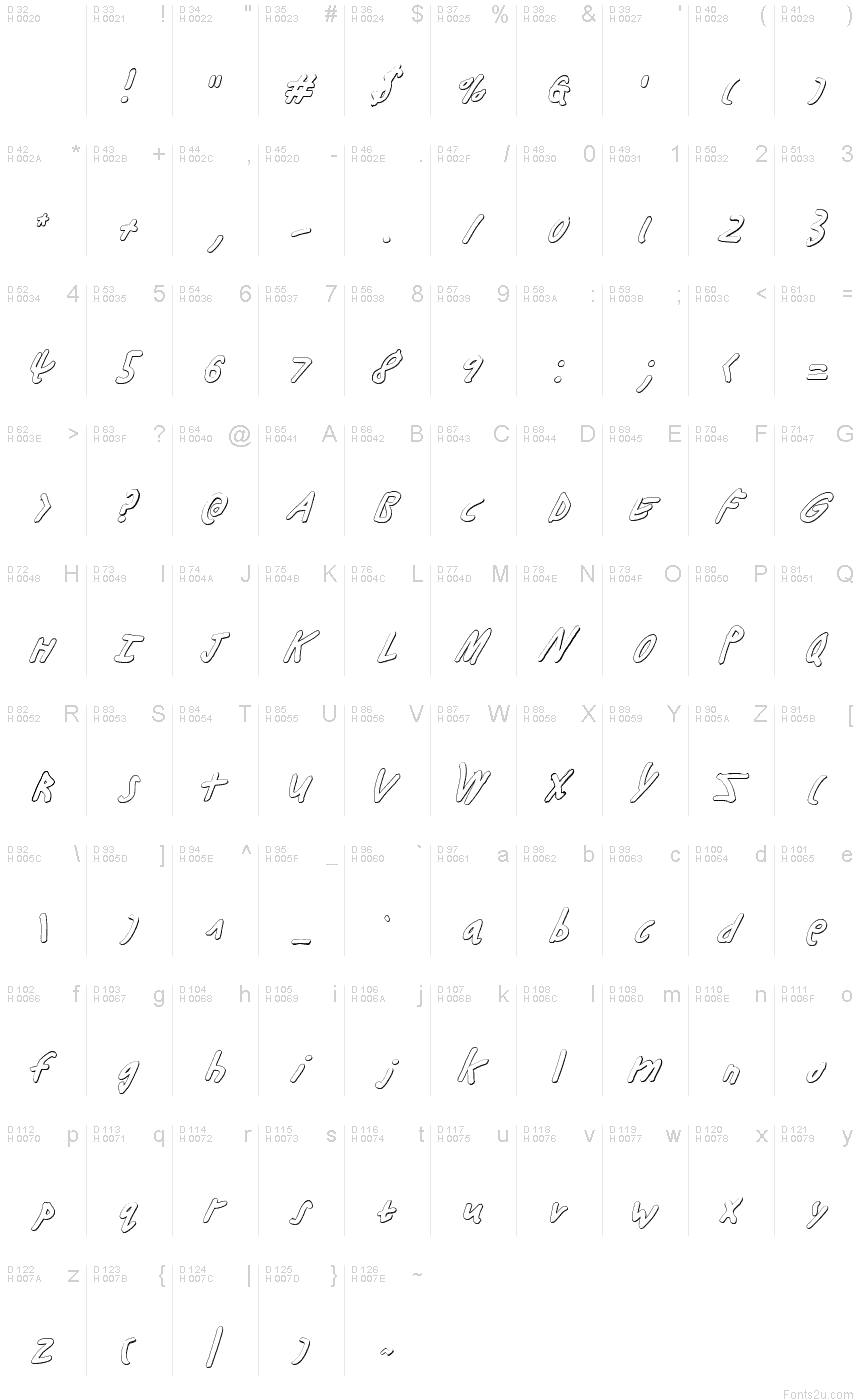
Buttons the Bear 3D Italic od Iconian Fonts to darmowy, zabawny krój pisma imitujący pismo odręczne, pełen kreskówkowego uroku. Litery pochylają się i pęcznieją niczym znaki nakreślone markerem, a wyrazisty cień 3D nadaje całości przyjazny, komiksowy charakter, unikając przy tym schematycznego efektu retro.
Świetnie sprawdzi się na okładkach książek dla dzieci, zaproszeniach, opakowaniach przekąsek, w komiksowych dymkach oraz na wesołych szyldach, gdzie łagodny, zaokrąglony pochył dodaje luzu. Jako darmowy font, idealnie nadaje się również do krótkich nagłówków, plakietek z imionami czy tytułów, ponieważ pękaty cień dodaje nawet prostym słowom nieco dynamiki.
Buttons the Bear 3D Italic